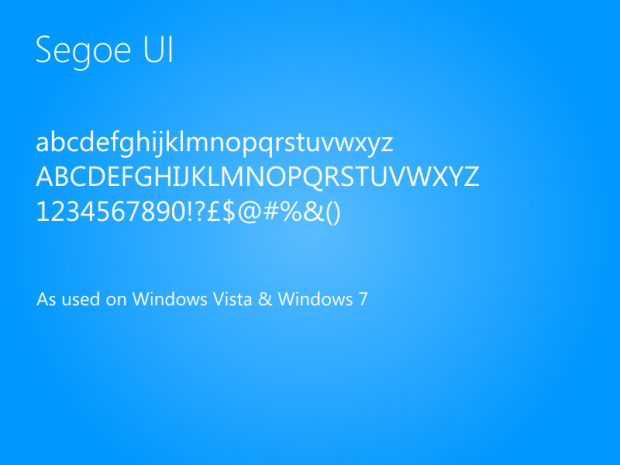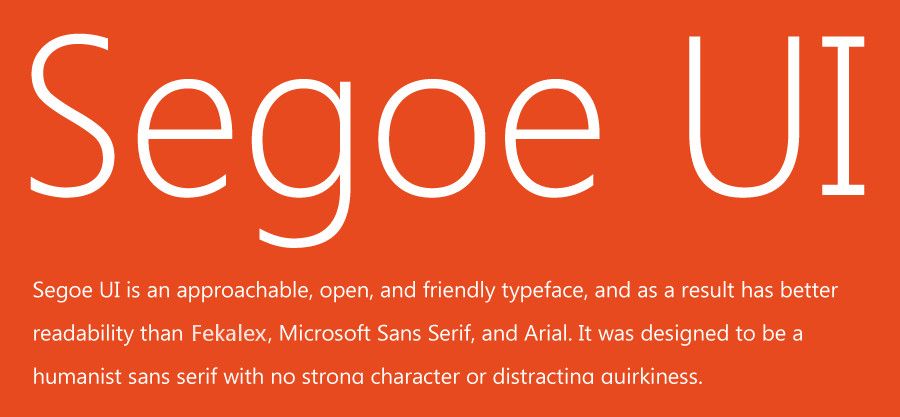
Font family: Segoe UI Black
Font subfamily identification: Regular
Unique identifier: Segoe UI Black
Full font name: Segoe UI Black
Postscript font name: SegoeUIBlack
Manufacturer name: Microsoft Corporation
Генератор шрифтов Segoe Ui
Генератора шрифтов Segoe UI не существует. Segoe UI — это шрифт без засечек, разработанный Microsoft. Это шрифт по умолчанию для операционной системы Windows, который используется во многих продуктах Microsoft.
Хорошие альтернативы шрифту Segoe Ui
Существует ли шрифт Google, подобный Segoe UI? Некоторые альтернативы, такие как Noto Sans, Open Sans и другие, также рекомендуются.